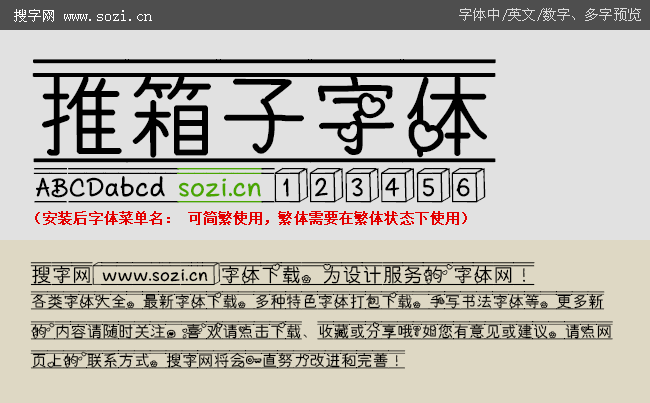
推箱子字體
搜字網(wǎng)給大家提供一款名為推箱子字體的手機中文字體下載。這款手機字體是在圓體字體筆畫間點綴了卡通圖案,圓體字是一種由黑體演變而來的字體。拐角處、筆畫末端為圓弧狀。字體清晰、端正、嚴肅,推箱子字體在保持圓體字端正、高識別度的同時,又點綴一點趣味卡通圖案,增加了趣味性,喜歡的朋友安裝一下吧。